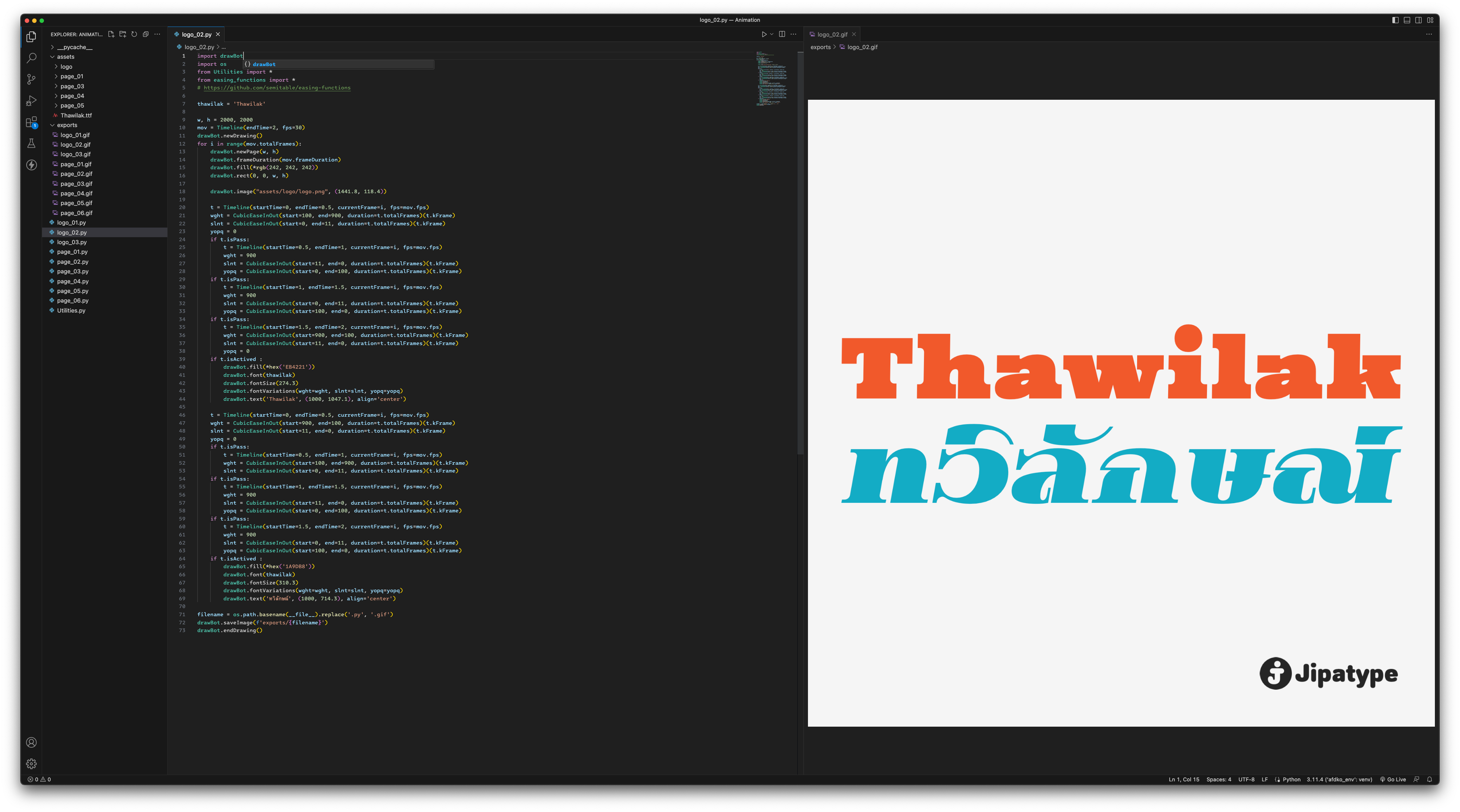
ทวิลักษณ์ | Thawilak
ชื่อฟอนต์ : ทวิลักษณ์ | Thawilak
ขอแนะนำ Thawilak ฟอนต์ยืดหยุ่นและหลากหลายที่ผสานความสง่างามของ Thawilak Serif เข้ากับความแข็งแกร่งของ Thawilak Slab ได้อย่างลงตัว ด้วยแกนสามแกน ได้แก่ Weight, Slant และ Y Opaque. Thawilak ช่วยให้นักออกแบบมีความเป็นไปได้ในการสร้างสรรค์งานที่หลากหลาย การผสมผสานของ Thawilak Serif และ Thawilak Slab ผสมผสานระหว่างส่วนโค้งที่สง่างามของ Serif และโครงสร้างที่แข็งแรงของ Slab ทำให้ได้แบบอักษรที่มีทั้งความประณีตและความแข็งแกร่ง ด้วยลักษณะที่แปรผันได้ Thawilak ช่วยให้นักออกแบบสามารถสร้างผลงานที่เป็นเอกลักษณ์ ตั้งแต่เลย์เอาสิ่งพิพม์ต์ไปจนถึงสื่อสำหรับสร้างแบรนด์ การออกแบบเว็บไปจนถึงบรรจุภัณฑ์.
Introducing "Thawilak" - a dynamic and versatile variable font that seamlessly merges the elegance of Thawilak Serif with the robustness of Thawilak Slab. With three axes - weight, slant, and y opaque - Thawilak empowers designers with a wide range of creative possibilities. Thawilak's seamless integration of Thawilak Serif and Thawilak Slab. The combination of the Serif's graceful curves and the Slab's sturdy, results in a font that exudes both refinement and solidity. With its variable nature, Thawilak empowers designers to craft a unique project. From layout documents to branding materials, web design to packaging.
แง่วว.. ต้องเขียนโค้ดเพื่อทำอนิเมชั่น ยังหาโปรแกรมอนิเมชั่นที่รองรับ VF ไม่เจอ  :0105:  :48: